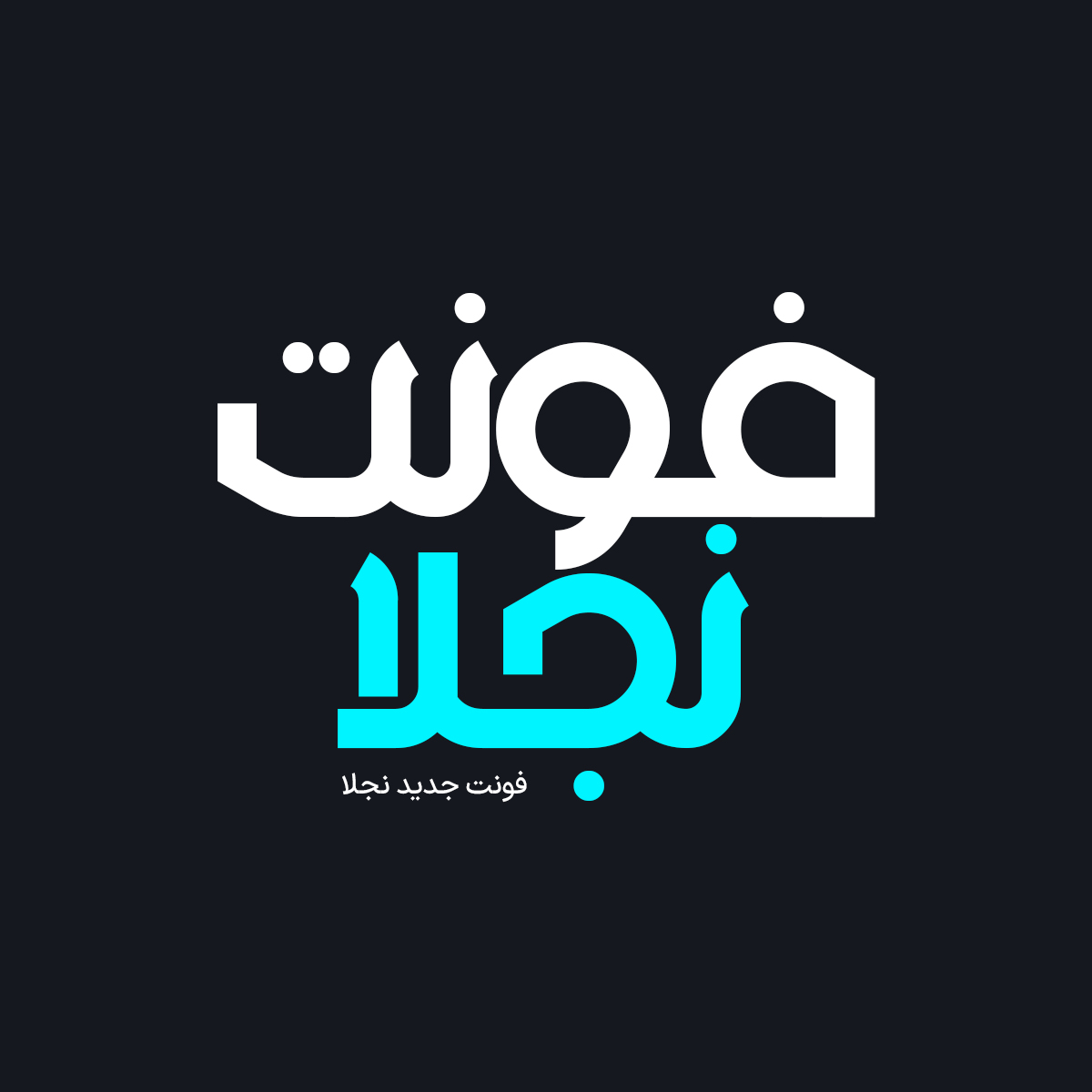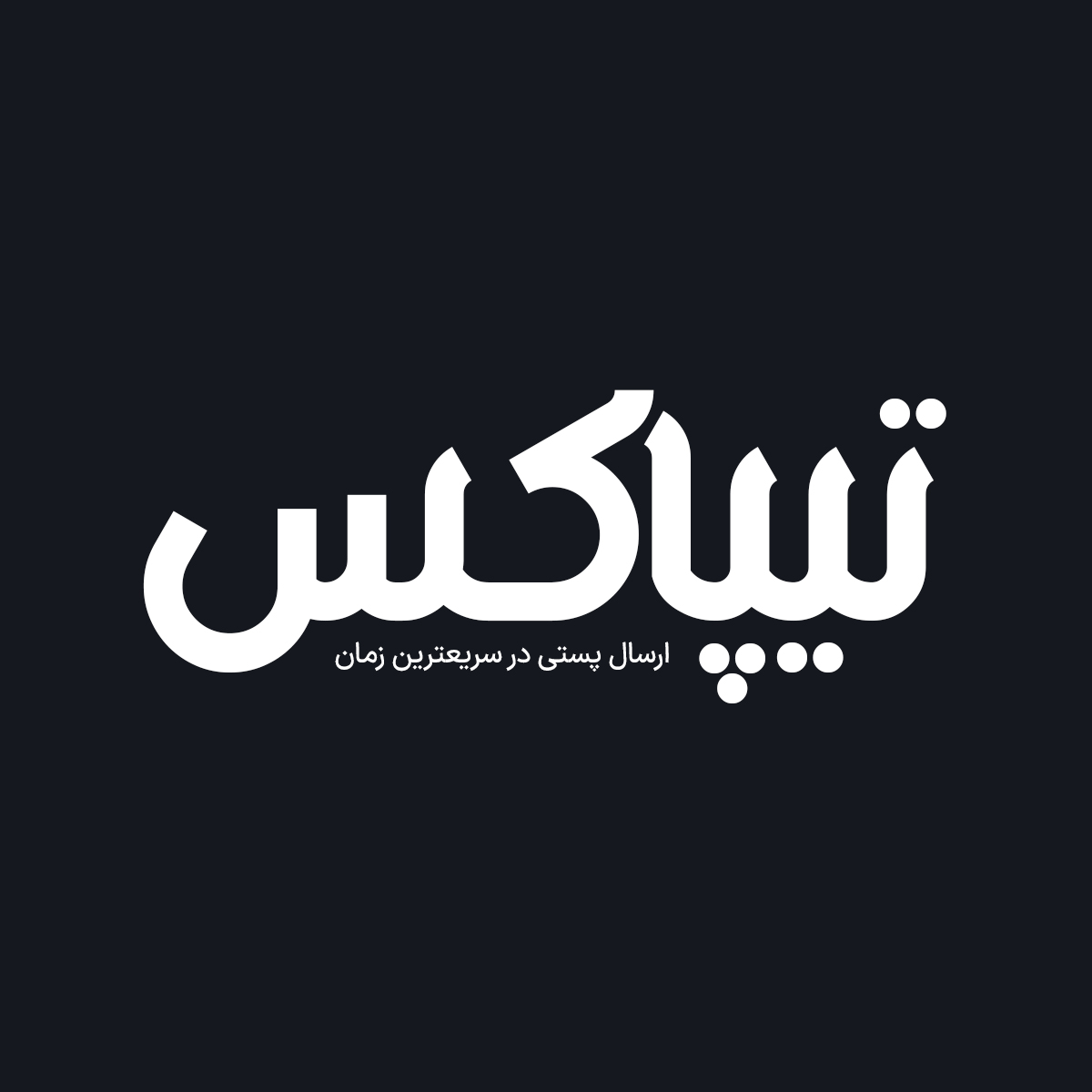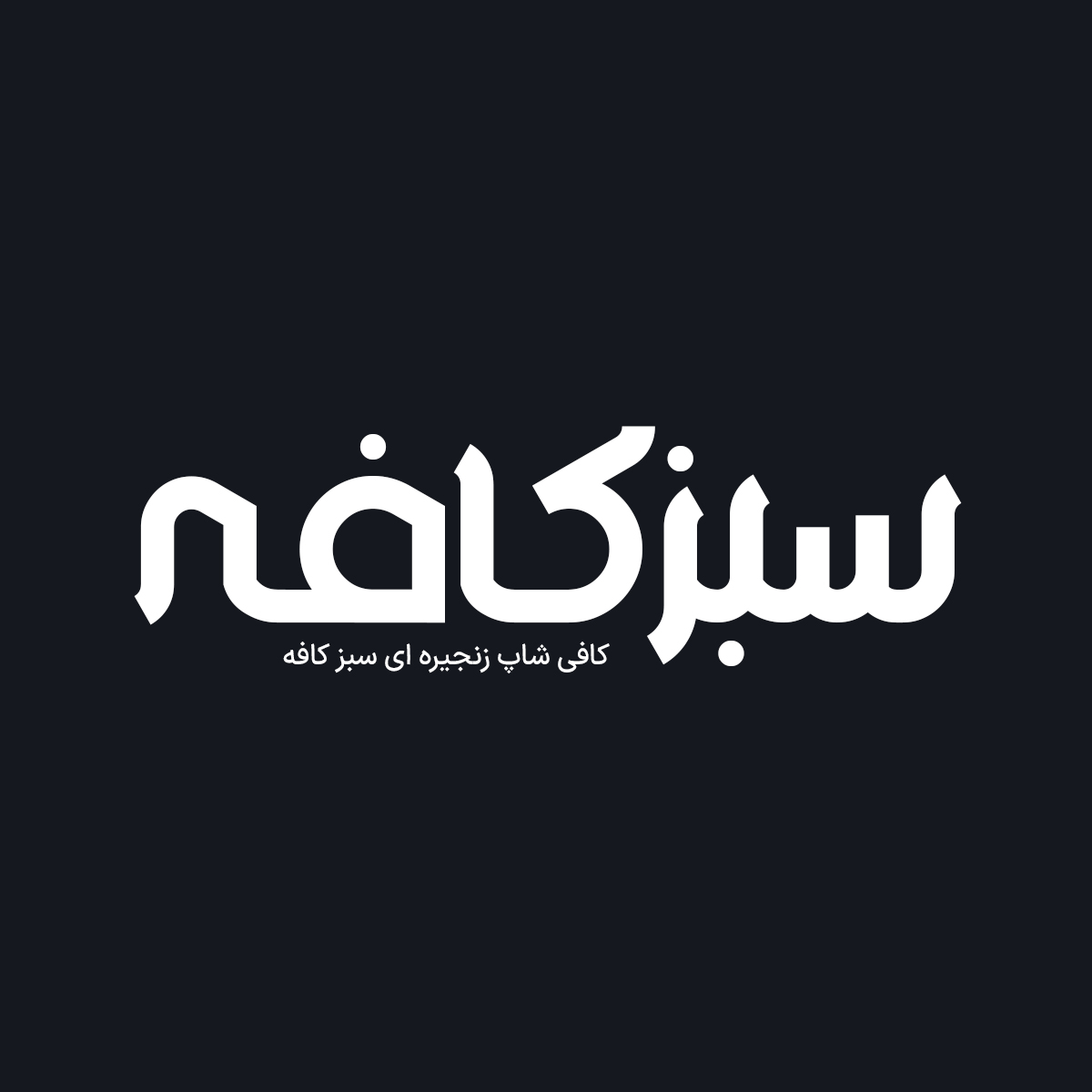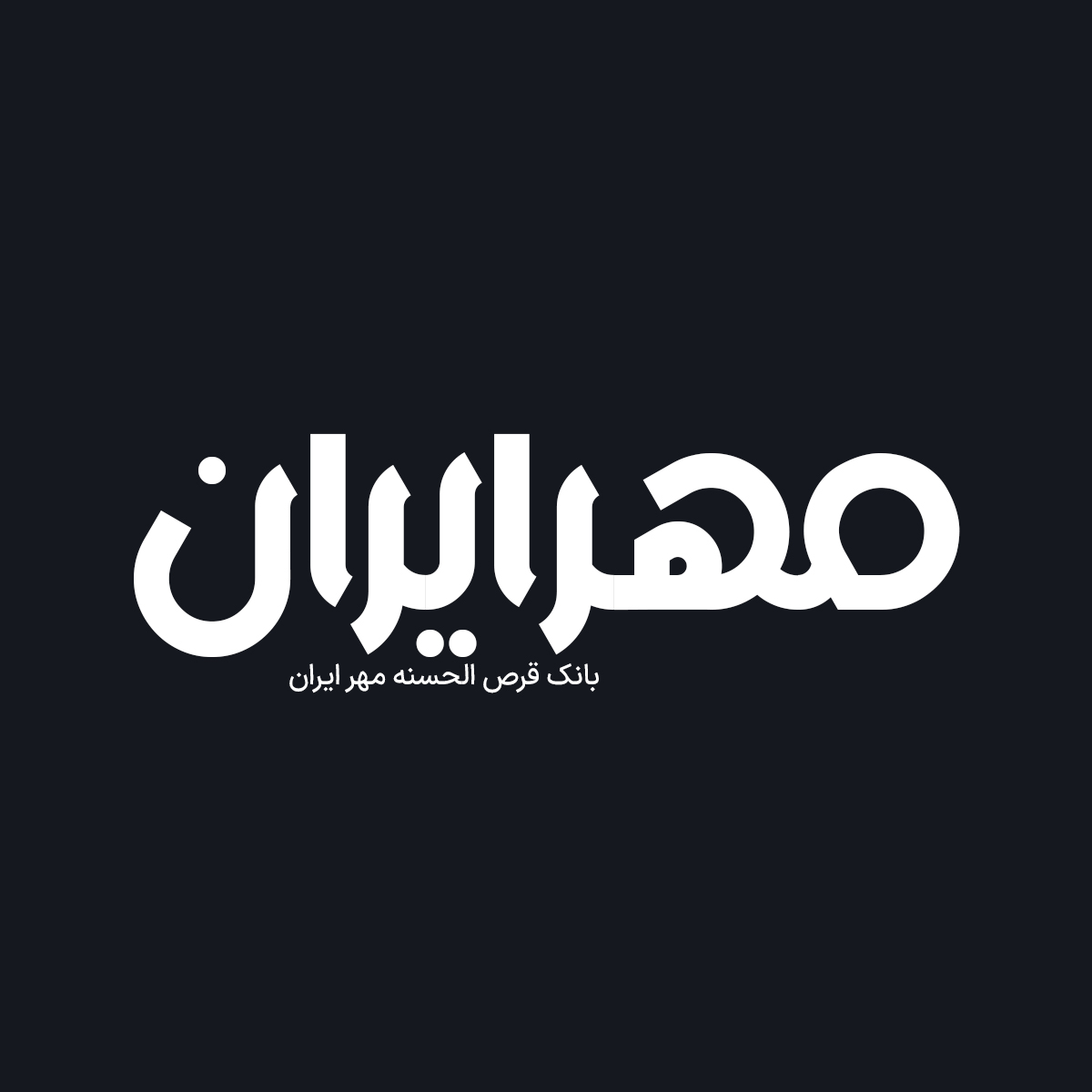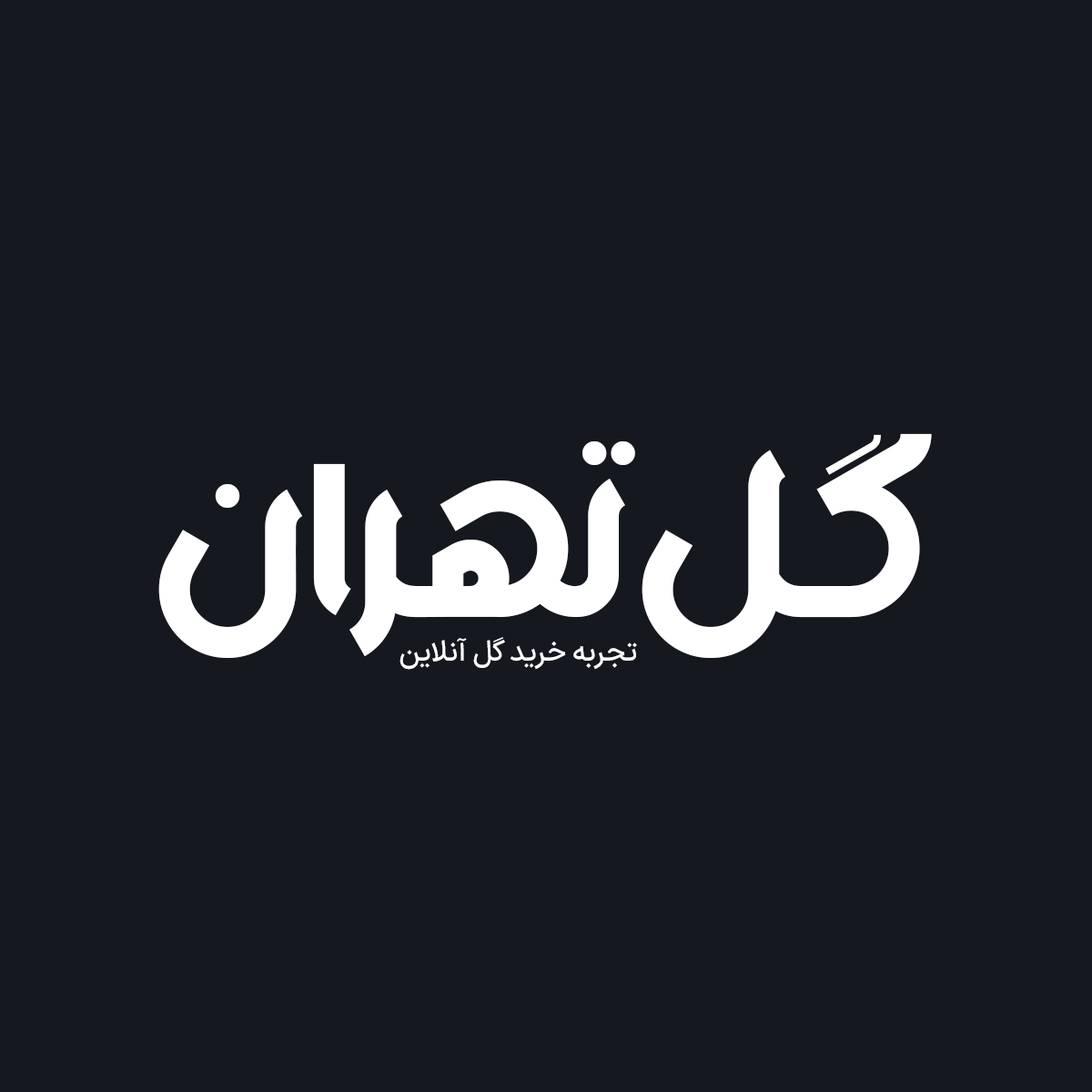
فونت فارسی نجلا Najla Font
فونت فارسی نجلا یک فونت فارسی بر مبنای حروف هندسی و خاص می باشد که به طراحان گرافیک امکان خلق طرح های زیبا و حرفه ای…
فونت فارسی نجلا یک فونت فارسی بر مبنای حروف هندسی و خاص می باشد که به طراحان گرافیک امکان خلق طرح های زیبا و حرفه ای به سادگی یک تایپ میدهد.
فونت نجلا یک فونت عربی، فارسی سازی و بهینه شده است که برای طراحی انواع امور گرافیکی به خصوص طراحی انواع لوگوتایپ و تایپوگرافی می باشد. از آنجایی که فونت هایی عربی فاقد حروف “گچ پژ” هستند و مشکلاتی در تایپ حروف “ک” و “ی” دارند در فونت نجلا حروف “گچ پژ” و همچنین اعداد فارسی و انگلیسی اضافه شده است و بعضی حروف بازطراحی شده اند تا بتوانید تمامی متن فارسی را به وسیله این فونت تایپ کنید. در ادامه برای شما نمونه تایپ های این محصول حرفه ای رو آماده کردیم که میتونید مشاهده کنید.
فونت نجلا دارای منحنیهای بسیار گرد با پایانه های بسیار تیز است که این فونت را زیبا، دوستانه، مدرن و خوانا میکند. فونت جزر با ارتفاع بالاتر از سایر فونتهای کلاس خود طراحی شده و برای متنهای طولانی، اندازههای کوچک و صفحه نمایش بهینه شده است تا خوانایی در ابعاد کوچک را در هر شرایط استفاده به ویژه برای فضای وب و صفحات دیجیتال واضحتر کند.
پیشنمایش و نمونه تایپ های فونت نجلا